続き。今度は U+6936 から U+8451 まで。
槱 U+69F1 GT/JKで組み立て方が違う。これは現在の版でも同様。 〈追記:U+2ACDD と重複?〉
殼 U+6BBC Vが「殻 U+6BBB」になっている。
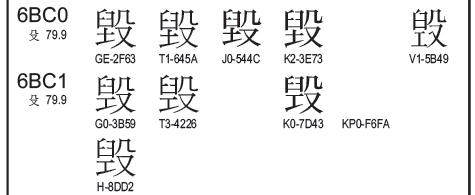
毀 U+6BC0 Vが「毁 U+6BC1」になっている。
潅 U+6F45 Tの字形が…?と思ったら、もともとこの形なんですね。へー。
礡 U+7921 Tが「礴 U+7934」(次項)になっている。これは現在の版でも存在するバグ。
礴 U+7934 Jだけ旁の組み立て方が違う(これも現在の版と同様)。ここに掲出されているのは JIS X 0212 の字体。
JIS X 0213 では
になったので、一応他と揃うことになる。
稷 U+7A37 Vの「田」の中が「メ」になっている。これはセーフ?
茦 U+8326 Vが
(U+2B1FF; 𫇿) になっている。
荢 U+8362 Jの「于」が「亍」になっている。「荢」は JIS X 0213 の 1-90-77。補助漢字には無し。
0213 の規格票では
なので、このドラフトの字形が誤り。日本のグリフにも誤字があるとは……。
菫 U+83EB Vが「堇 U+5807」になっている。